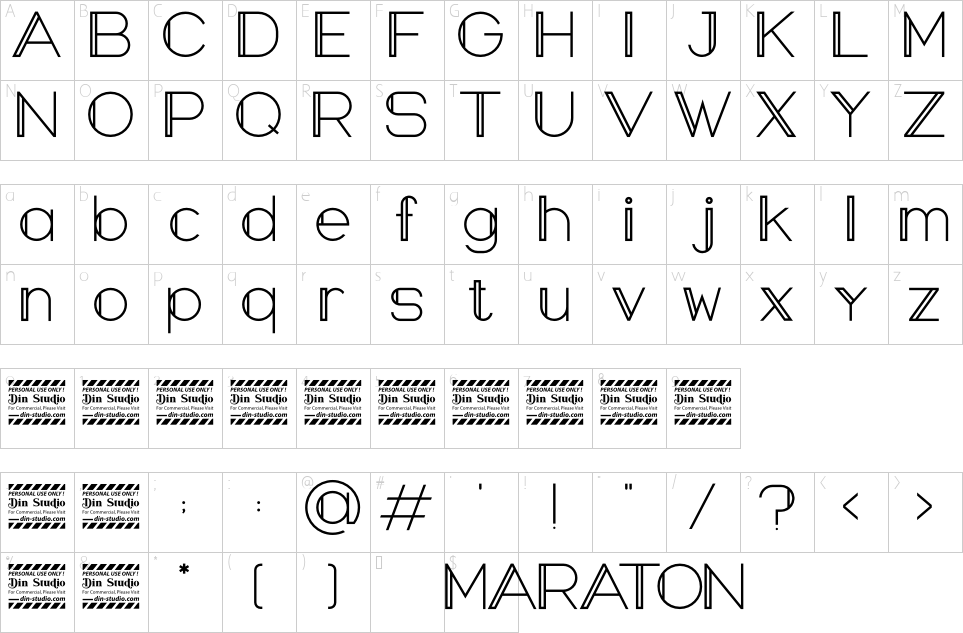
A fonte Maraton é uma opção única para designers gráficos, oferecendo uma ampla gama de opções para criar design. Sua designer, Din Studio, apresenta essa fonte em um design moderno e versátil que pode se adaptar a um amplo espectro de projetos. Com mais de 7.250 downloads, Maraton é uma fonte popular entre designers que valorizam uma variedade de opções de estilo e tamanho. Se você está procurando por uma fonte que se destaca e que ofereça flexibilidade para criar design variado, Maraton é uma excelente escolha. Esta fonte Windows e Mac foi projetada para atender às necessidades de designers profissionais, oferecendo uma solução prática e versátil.